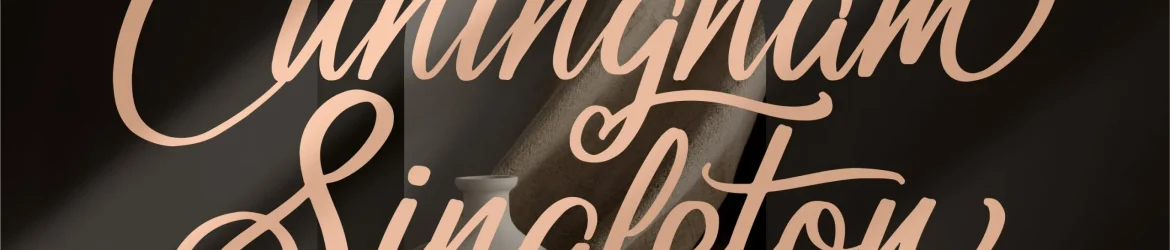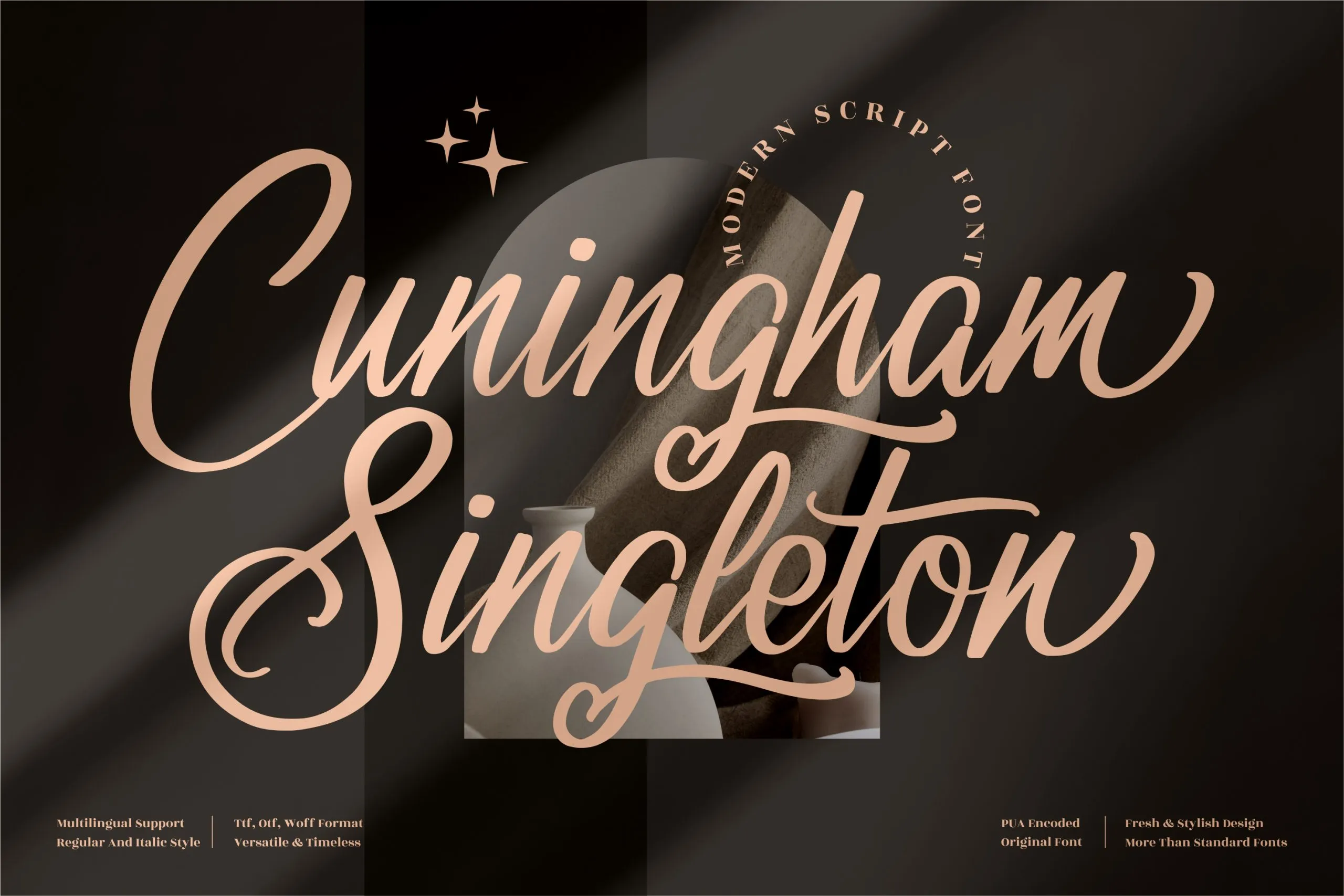
Cuningham Singleton Font
Esta é uma fonte de registro ideal para projetos sofisticados como logotipos, embalagens de produtos, nomes no card, convites e cartões de visita, mugs personalizados, capas de livros, adesivos, tags, cortinas, etiquetas, materiais publicitários, selos, papelaria e muito mais. A fonte Cunningham Singleton foi criada pelo designer perspectype com um toque elegante que se adapta perfeitamente a qualquer projeto em que você precise de uma aparição premium. Seja para revestir uma embalagem sofisticada ou personalizar um tênis, este é o tipo certo. A Cunningham Singleton oferece nuances e detalhes impressionantes, tornando-a uma escolha segura para os mais exigentes projetos criativos do design gráfico.